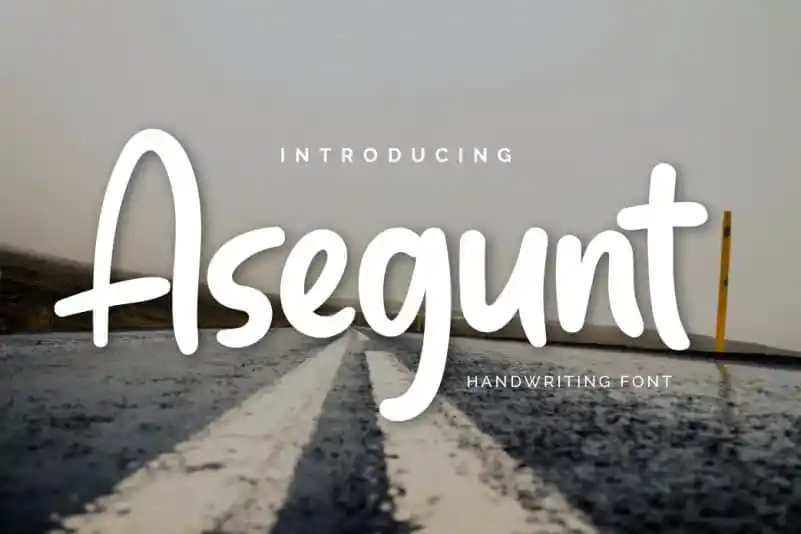
Asegunt Handwritten Font – Download Grátis
Asegunt Handwritten Font é uma bela fonte escrita à mão abstrata que traz a essência natural do estilo ao seu projeto visual. Desenhada pelo criador twinletter, esta font permite criar textos e frases com uma mistura única de traços escritos à mão originais. Ela se destaca por sua simplicidade elegante e por conter nuances únicas que a tornam um recurso gráfico atraente para designers digitais ou criadores de conteúdo online. Com suas linhas fluidas e desenhadas com amor, Asegunt pode transformar qualquer texto em uma peça visual autêntica e vibrante. Focado no estilo handwritten, a fonte oferece uma experiência única que se aproxima da forma como as pessoas expressam sentimentos e pensamentos por meio do papel — um aspecto intrinsecamente humano da comunicação visual. Seja para criar anúncios capturadores, blogs intrigantes ou até mesmo designs de site com o estilo certo, Asegunt Handwritten Font é uma escolha perfeita para adicionar vida a qualquer design. Combinada com outros recursos gráficos, essa fonte escrita à mão ajuda os designers a expressar sua visão em um nível ainda mais profundo e emocional.